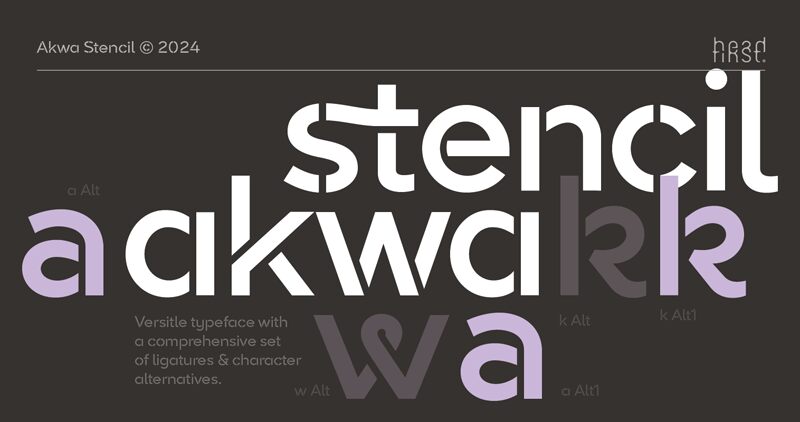
Die AkwaStencil Bold von Morice Kastoun (Headfirst Design) aus der AkwaStencil-Familie ist eine kostenlose, dekorative Military-Stencil-Schrift. Sie überzeugt mit präziser, blockartiger Geometrie und klaren Aussparungen, die an frische Sprühfarbe auf einer Versandkiste erinnern – markant, stabil und sofort industriell. Die breiten Formen bleiben selbst in großen Größen hervorragend lesbar, damit Ihre Botschaft direkt ins Auge sticht.
Mit der AkwaStencil Bold erzielen Sie starke Ergebnisse auf Postern, Apparel-Designs, Albumcovern, Event-Beschilderungen, Verpackungsstempeln sowie Titelkarten für Spiele oder Filme mit taktischem Anspruch. Diese kostenlose Schrift glänzt auch auf Badges und Labels, bei denen es auf schnelle Erkennbarkeit ankommt. Kombinieren Sie sie für Begleittexte mit einer schlichten, kompakten serifenlosen Schrift und erhöhen Sie bei großen Schriftgraden den Zeichenabstand leicht, damit die Stencil-Brüche atmen können.